内容については全く知らないが、前半の「東行初録」「東行続録」「東行三録」は、1882年あたりの朝鮮のことが書かれている様子。後半は「甲午戦事電報録」と「馬関議和中日談話録」。
本文は繁体で、こんな感じ。段落の頭は2字下げ。
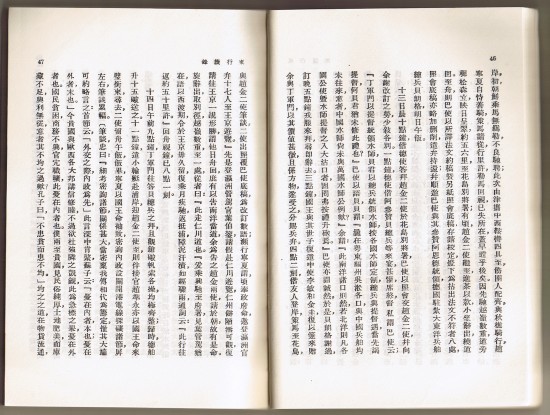
左上を拡大。約物の組み方が独特。初めて見た。
このように【,。!?:;】の6つは、文字のすぐ右隣に組まれている。ざっと見たところ【、】は使われていなかった。
鍵括弧は「『』」ではなく『「」』の順で使われている。日本のものと比べると、ボディの真ん中寄りに作られている感じ。数箇所しか出てこないが、補足などには()ではなく〔〕が使われている。こちらは上の画像の通り、内側に寄っている。やや小ぶり。
禁則処理の例。行末に【『】がくるのを回避するため、四分のアキを4つ入れて追い出している。この方法は日本でも見る。
普通では禁則処理の対象となる【,。!?:;】は文字の横に組まれているため、考慮する必要があるのは【『』「」〔〕】だけとなる。実際にページをパラパラめくってみても、禁則処理の箇所はかなり少ない。この点を考えると、なかなか合理的な組み方。